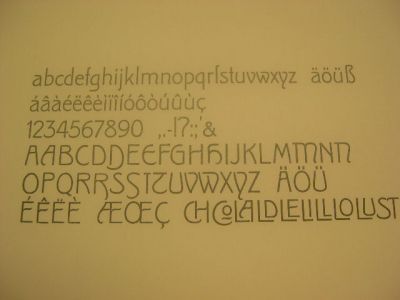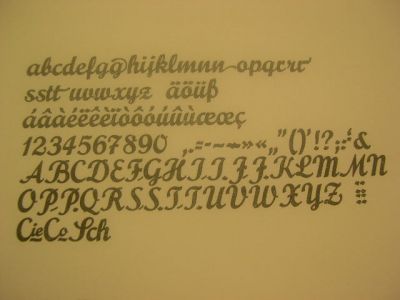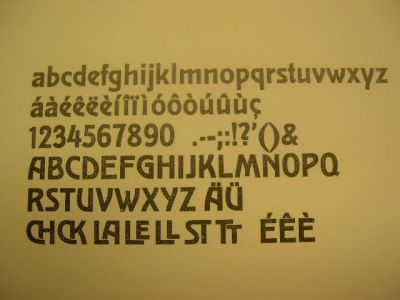
Schriftbild - Stilepochen Zuordnung
In welcher zeitlichen Stilepoche wurden vorrangig in
Texten Schmuckelemte wie Alternativ-Buchstaben,
Superiors, Nester, Ligaturen etc. benutzt?
Ich denke da zum Beispiel an ein Schriftbild wie es
in dem Bild mit der Mantinia von Matthew Carter
In Deutschland gab es in der Jugendstil-Zeit häufig solche Ligaturen.
Kleopatra - Bauersche Gießerei, Frankfurt am Main
Hausschnitt - Erstguß 1912
Das hier ist wohl schon etwas spät für Jugendstil:
Prägefest - Ludwig & Mayer, Frankfurt am Main
Erstguß 1926 - Eduard Lautenbach
In der Zeit des Jugendstils gabt es zwei Richtugen, eine historisierende und eine moderne. Solche kreativen Zeichen sieht man schon auf alten Steinen. Wenn der Steinmetz merkte: Oh, ich komme mit dem Platz wohl doch nicht hin. oder Mißt, es fehlt ein Zeichen. hat er eben zu solchen Mitteln gegriffen und oftmals haben sie auch Charme. Dies setzte sich in den handgeschriebenen Büchern fort. Also war es nie wirklich aus der Welt. Um 1900 wurden solche Dinge exzessiv wieder aufgegriffen, besonders in Werbeschriften und eben typischen römischen Versalschriften.
Das Ursprungsmuster des Erstbeitrages war ein Beispiel aus den VSvA(?) oder England? Meinst Du, die Entwicklung lief damals parallel oder gab es wohl gegenseitige (oder vielleicht auch nur einseitige) Einflüsse?
Ja, natürlich lief vieles gleichzeitig und beeinflußte sich gegenseitig. Die damalige Designszene war bestens organisiert, informiert und international. Man schaue sich nur die vielen alten Zeitschriften an, die von Fachleuten für Fachleute gemacht wurden, oft sogar zweisprachig.
Zum Muster oben, das sieht mir nach einer sehr neuzeitlichen digitalen Type aus. Solche Schriften wird es immer wieder neu geben, es macht einfach zu viel Spaß als Schriftgestalter damit zu experimentieren.
Das, das Beispiel oben ist von Matthew Carters Mantinia Schrift. Diese Schrift war von ihn in den 1990ern gemacht.
Georg: Matthew Carter ist Englander, arbeitet aber seit Jahrzehnten in den USA. Ich weiß es nicht, wer genau den Muster gelayoutet hat. Aber der war wahrscheinlich in den USA auch produziert. Es sei denn, das Bild handelt sich um ein Examplar aus einer deutschen Designzeitschrift oder Webseite.
Gerade frisch klassifiziert und gedruckt.
Ich dachte, ich zeige sie Euch, weil sie auch sehr interessante Versal-Ligaturen aufweist.
Das ist eine Halbfette Skulptur von der Schriftgießerei Emil Gursch, Berlin. Der Erstguß hat um 1900 herum stattgefunden, genauer konnten wir es nicht herausfinden.
Weiß jemand ob es die Skulptur auch in digitaler Form gibt?